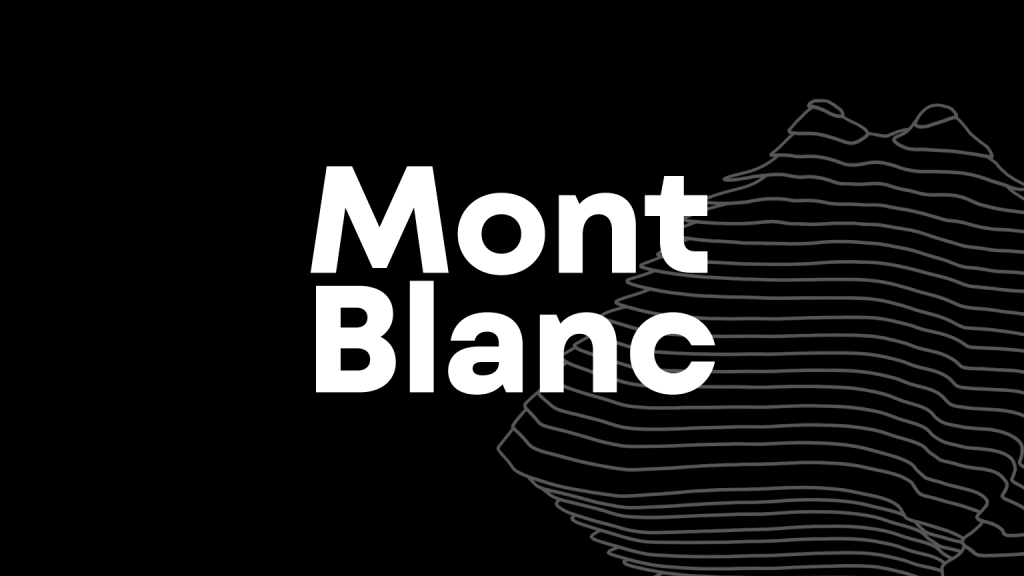
Phân loại: Sang trọng
Montblanc Font không chỉ đơn thuần là một phông chữ, mà còn là biểu tượng của sự sang trọng và đẳng cấp trong thế giới thiết kế. Montblanc Font là font chữ thuộc bộ font chữ không chân. Được lấy cảm hứng từ thương hiệu bút danh tiếng Montblanc, phông chữ này thể hiện sự tinh tế và thanh lịch, phù hợp cho các dự án đòi hỏi sự trang nhã. Với thiết kế chữ rõ ràng, thanh thoát, Montblanc Font không chỉ làm nổi bật nội dung mà còn mang lại cảm giác chuyên nghiệp, thích hợp cho các ấn phẩm cao cấp và thương hiệu sang trọng.